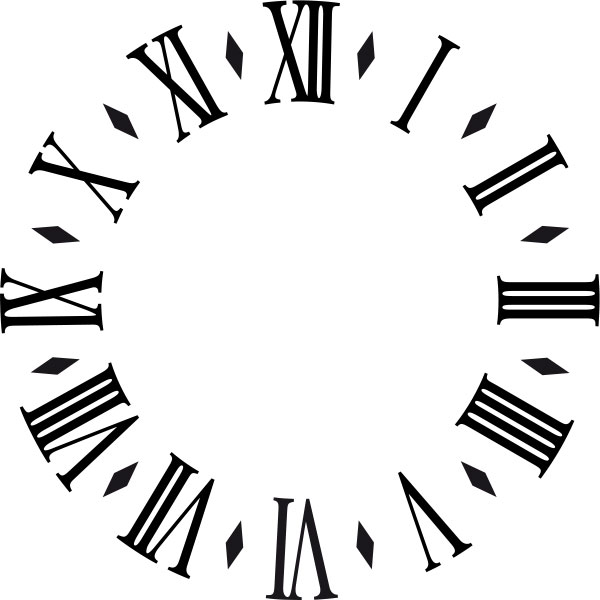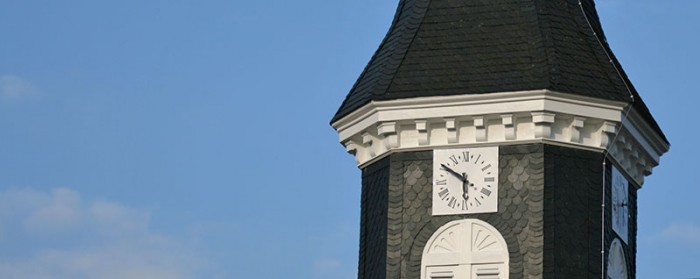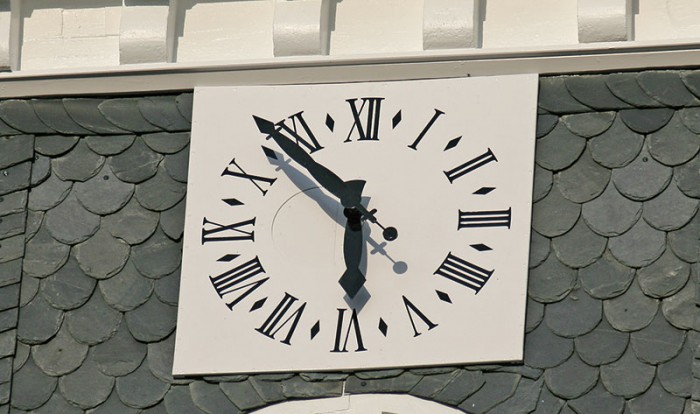
Schmallaufende römische Ziffern
Meint ihr mit der Verzerrung wegen der Froschpersektive diesen Gedanken, den ich hier mal nach Albrecht Dürer zitiere:
Es begibt sich oft das man schrift an die seulen / thürn / oder an hohen maueren macht /darumb welicher an ein an ein thuren schreyben will das man die oberst zeyl der buchstaben als wol gesech zu lesen als vnderst / der mach sie oben größer dann vnden / durch ein solichen weg / stell dein gesicht so weyt von dem thurn / vnd in der hoch wie du wild / diß sey ein punct.c.vnn nym für dich den weg des dryangels.a.b.c.der.16.figur des lini büchleins / vnn las das.a.b.sein die thuren höhe oder want darauf du schreyben wild. Nun teyl in das cirkeldrum.b.e.mit puncten gleych weyten der zeylen Darein du schreyben wild / vnnd als dann far auß des gesichtz puncten.c.mit geraden linien durch all puncten des circeldrums.b.e.biß an die aufrecht thuree höhe oder want.a.b. Darnach far mit parlinien auß disen puncten auf des thurns want vber zwerch. Zwischee die selben linien must du dein schrift setzen / da wirdt dir anzeygt wie vill die öberen bustaben grösser werden dann die vnderen / vnnd so du aber ein kurtze lini nach der langen.a.b. gleychmesig wild teylen / so reyß all linien gerad in den punctee.c.vnd schneid sie mite iner aufrechten parlini.f.g.gehen dem puncten.c.ab.so wird.f.g. gleych geteylt wie.a.b. mit der sie ein parallel ist. Diß ist zubrauchen im für oder hindersetzee zu ergrössen oder kleiner machen. Also sind all lini nach anderen zu teylen in gleychen oder vngleychen dingen / vnd in den teylen die man nit nenne kan / vnn soliche teylung hat nit allein stat in den pustabe / sondern in allen andere dingen / vnn in sonders so man einen hohen thuren in allen gaden nit bildwercken ziree will / also dz die oberen bild gleych den vnderen scheynen kan durch disen weg geschehen / wie das hernach aufgerissen ist.
(wenn ich das jetzt auf aktuelles Hochdeutsch übersetzen soll, bitte sagen)
PS: Zudem hat sich mir jetzt geklärt, was es mit den in eiem anderen Strang mit den Punkten vor und nach Zahlen auf sich hat: Es war damals praktisch eine Art Klammer um die Zahl - bzw hier im Text um die Bezeichnung der Punkte.
Statt wie wie heute schreiben würden „das Dreick (a b c))“ schrieb man damals „das dryangel.a.b.c.“
Ja, so ungefähr, obwohl es bei Dürer ja mehr um einen Größenausgleich von Zeichen in unterschiedlicher Höhe geht, und Kathrin wohl eher eine perspektivische Verzerrung meinte.
ich würde lediglich die Füße edr Is in VII einen Hauch an das V ziehen, evtl auch bei VIII
Ein Hauch geht immer.
Ich vermute, daß die Abstände zwischen den I ( in II, III, IIII, VII, VIII und XII) zu eng sind und bei dem großen Betrachtungsabstand einer Turmuhr nicht funktionieren. Das war zwar beim Original auch nicht besser und man könnte das auch mit dem Argument ignorieren, daß bei einer Uhr ohnehin jeder weiß, welche Ziffer wo steht, aber ich würde die Abstände noch ein bißchen aufbohren.
Ich suche eben den Kompromiss. Mache ich den Abstand zwischen Is größer wird die Zahl breiter, wir die Verzerrung größer.
Und: ja, man schaut sich die Zahlen eigentlich nicht an. Mir ist erst jetzt, wo ich das Ziffernblatt in Händen hielt, aufgefallen, dass die Vier als IIII und nicht als IV geschrieben wurde, obwohl ich seit Jahren an dem Turm vorbeigehe und auf die Uhr schaue.
Ich fand auch dieses Blatt hier. Dort wurde die Zentrierung drastisch gelöst:
zentriert 1
Ab 7 Uhr gibt es nur noch eine große Zahl
zentriert2
Auch ’ne Art der Verzerrung
zentriert3
Es gibt die Zentrierung wohl auch bei Turmuhren …
zentriert4
… und bei Bahnhofsuhren
Dem Parallax-Effekt kann man bei Turmuhren nicht entgegenwirken, weil es ja nicht den einen Betrachtungswinkel gibt. In diesem Falle gibt es Positionen im Städtchen, wo man auf einer Höhe mit der Turmuhr steht.
Ich wollte doch noch schnell das Ergebnis zeigen, auch wenn die sache schon etwas älter ist. Vom Boden aus erkennt man kaum Details, man kann fast noch nicht einmal die Ziffern an sich unterscheiden. Dazu ist das Zifferblatt zu klein. Das Teleobjektiv täuscht hier mehr Details vor.
Nun ja, alte Schriftmusterbücher hätten in meinem Fall ja  noch einen praktischen Nutzen. Zeiger dagegen sind dann höchstens Dekorativ, es sei denn, man hat selbst einer Turmuhr, die dringend mal einen neuen Zeiger braucht.
Ihr denkt viel zu conservativ. Als obrigkeitlich anerkannter Hacker™ muß ich sagen: So ein großer Zeiger ist ein erstklassiger Bidenhänder, der kleine ein brauchbarer Gladius, und solche kann man in unruhigen Zeiten schließlich immer mal gebrauchen.
Was macht man mit den Uhrzeigern einer Kirchturmuhr?
Na an die Wand hängen, würde ich mal vermuten. :-?
Ist übrigens schön geworden, dein Zifferblatt! :biglove:
Ich hab mal versucht, etwas systematischer an das Ziffernbalt heranzugehen. (Als ich den Job angenommen hatte, war ich von "schnell mal ein paar Zahlen in den Kreis setzen" ausgegangen)
Wenn die Anpassung an die Rundung vorgenommen wird (und das muss sie ja), dann muss ich mit Verzerrungen leben.
Sieht man sich andere Ziffernblätter an, so erscheint die Verzerrung weniger aufzufallen, wenn:
1) die Ziffern nicht so breit sind. Ist ja klar, dann kommen sie nicht so weit weg von der eigentlichen Mitte der Zahl. Bei Taschenuhren wird das bisweilen sehr extrem gemacht, wie auch bei dem Bildchen von catfonts. Bei einer Turmuhr, so sehe ich das, darf es nicht zu eng werden. Ich blicke auch immer mit einem Auge auf die alte Vorlage.